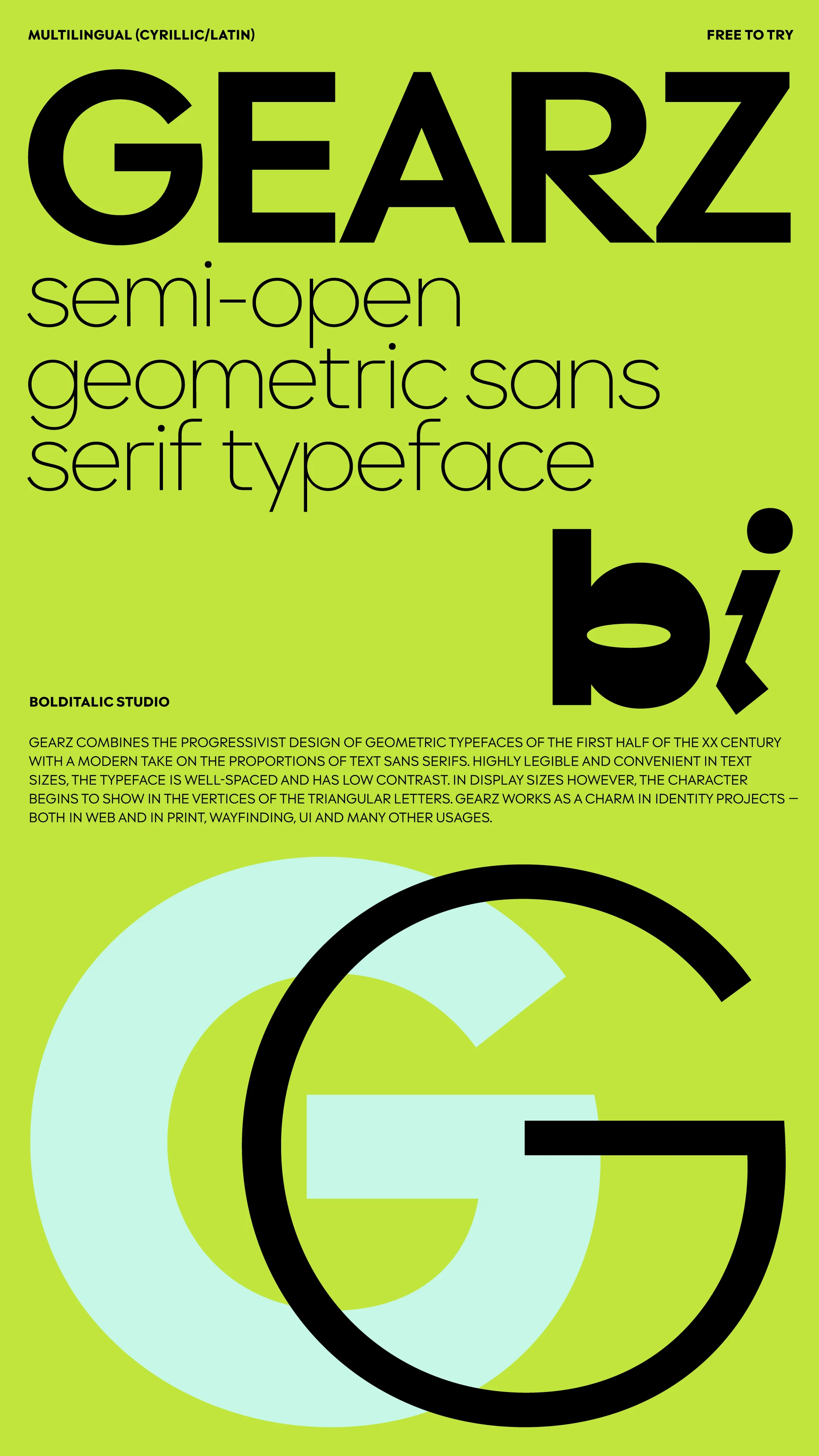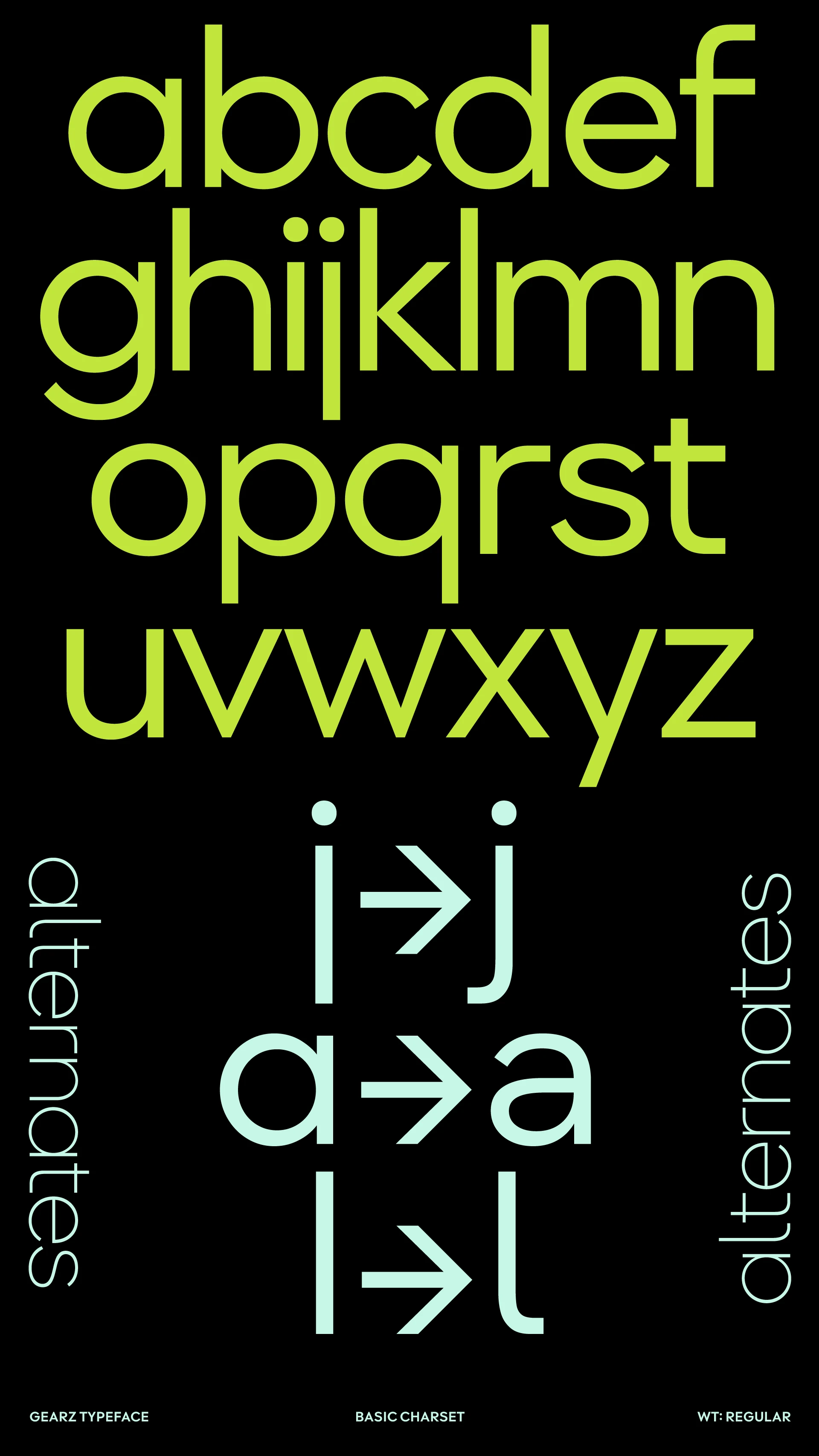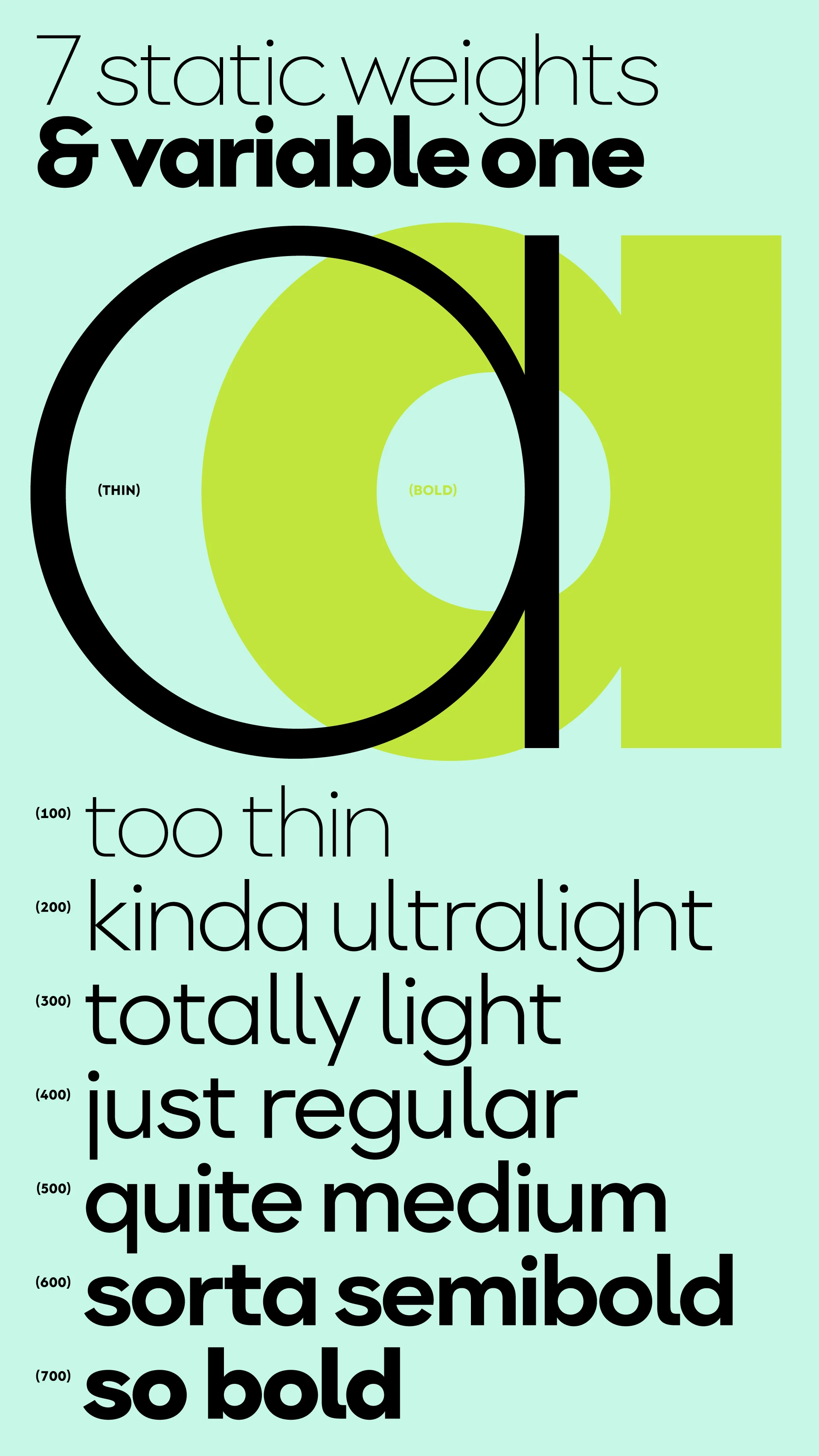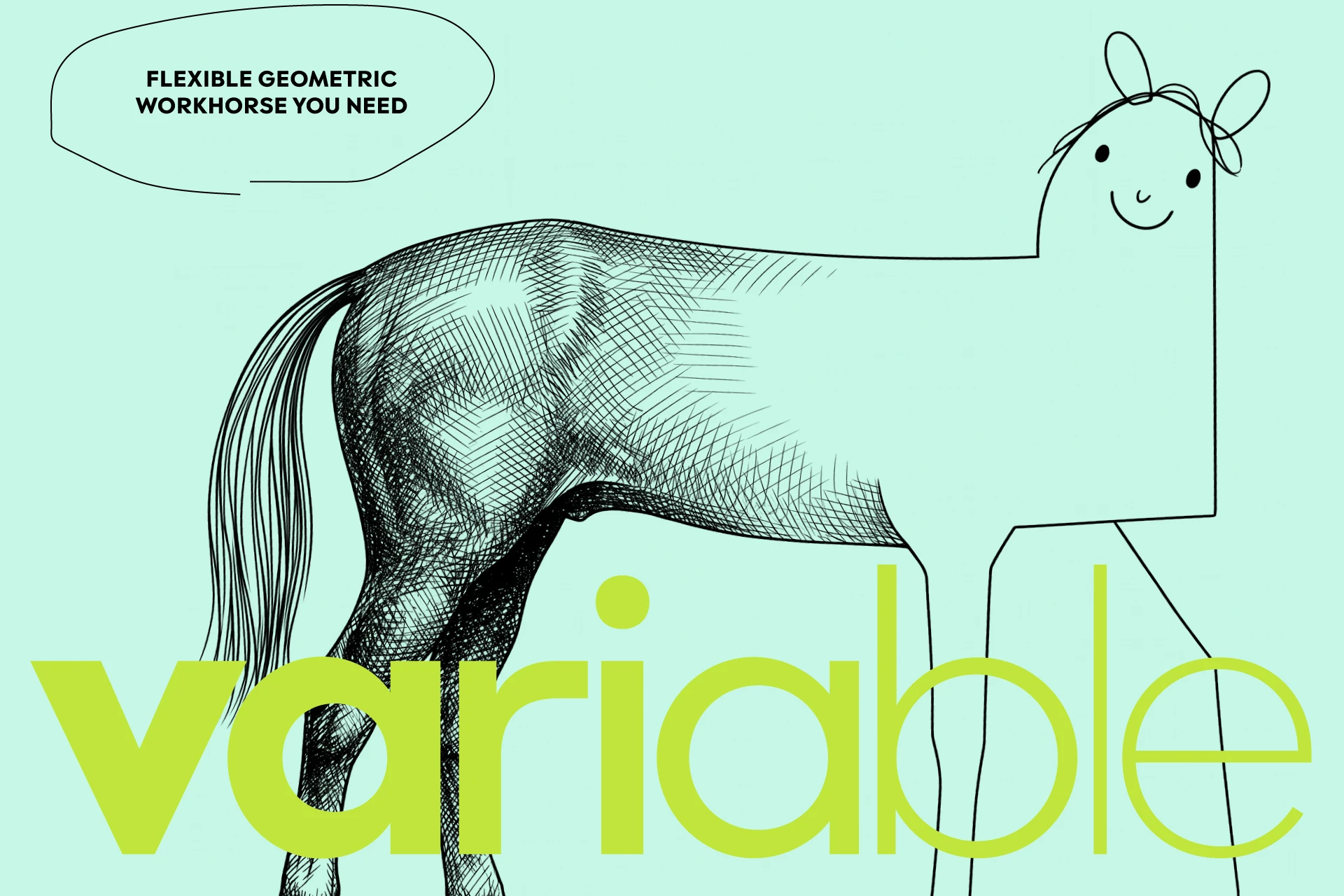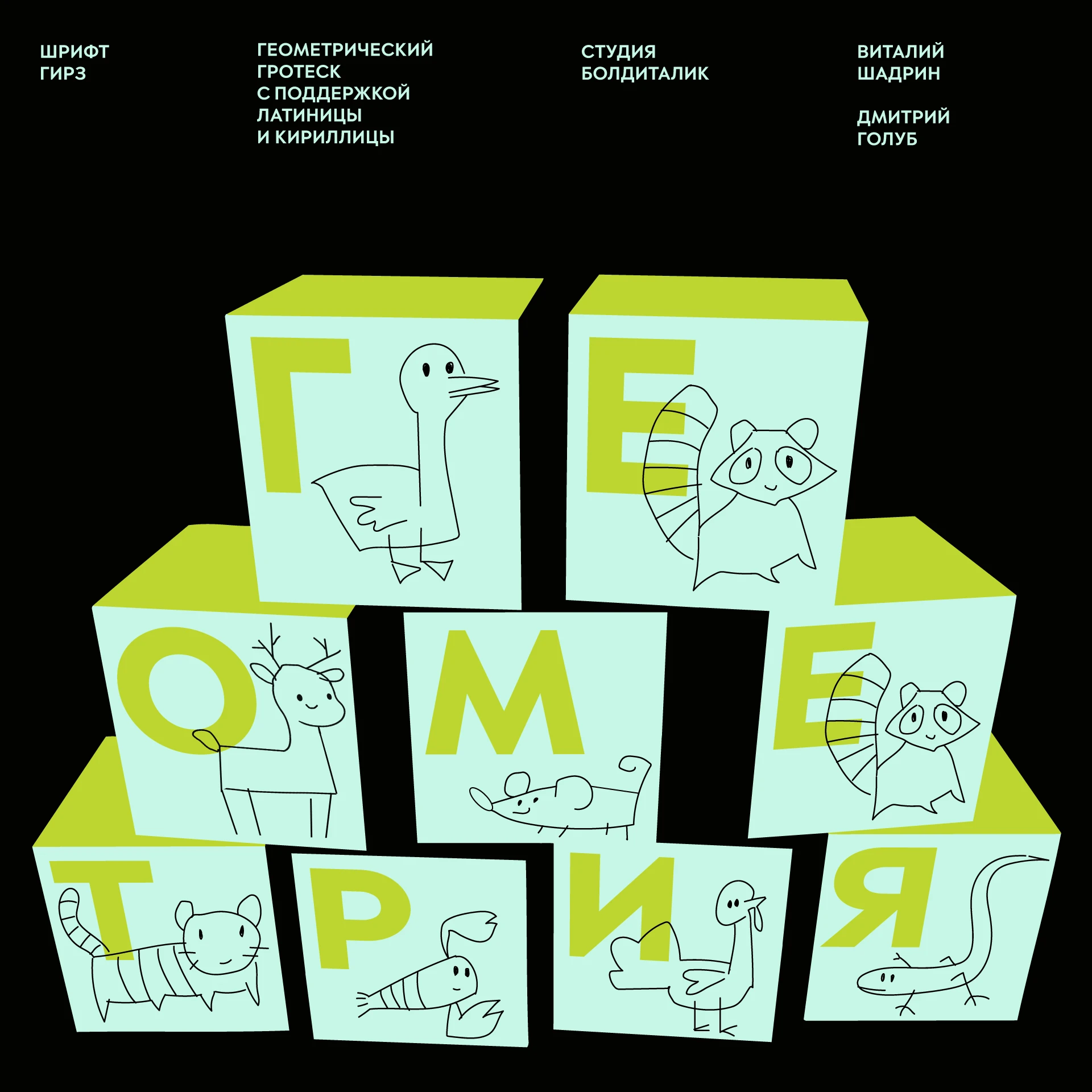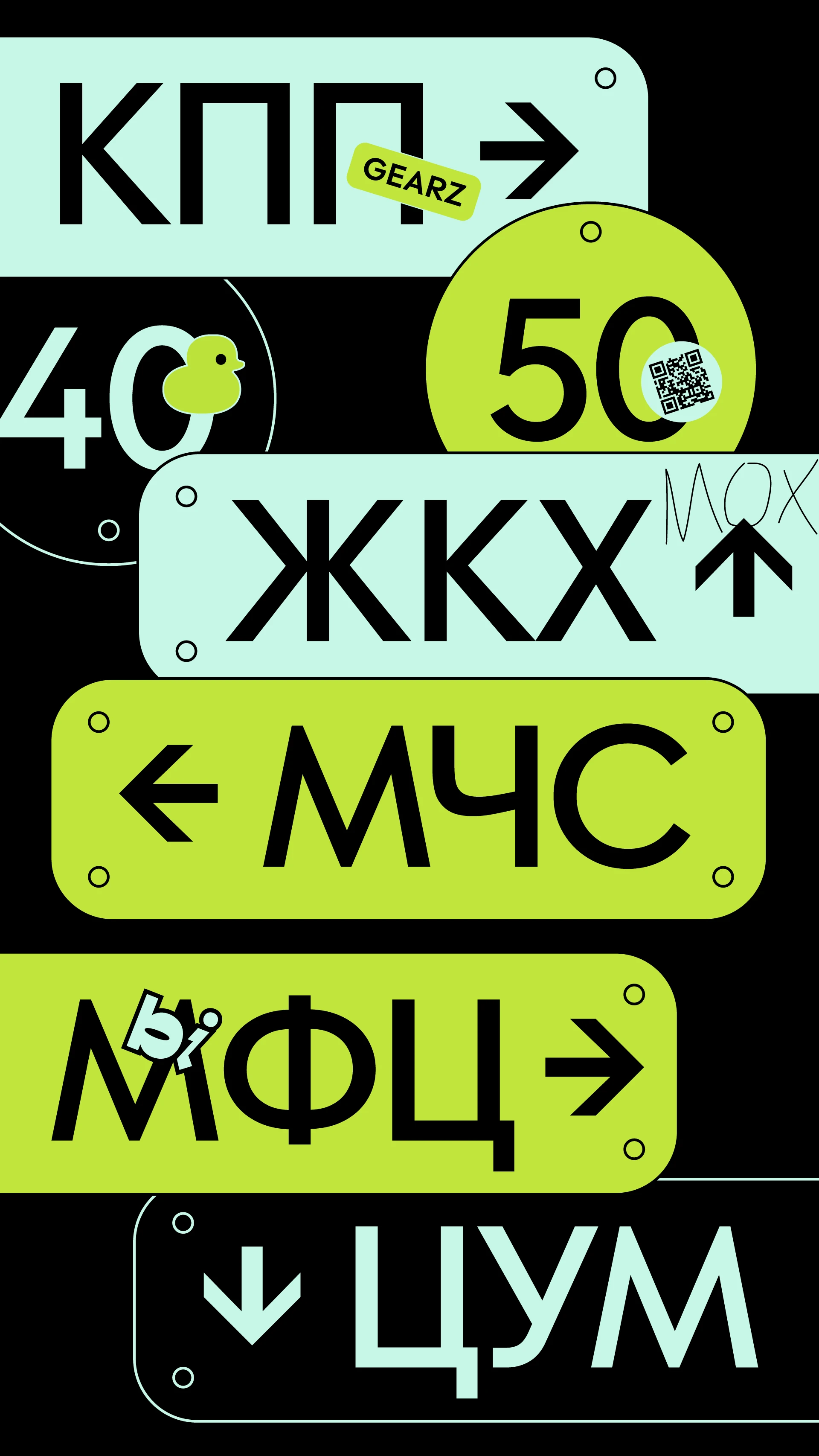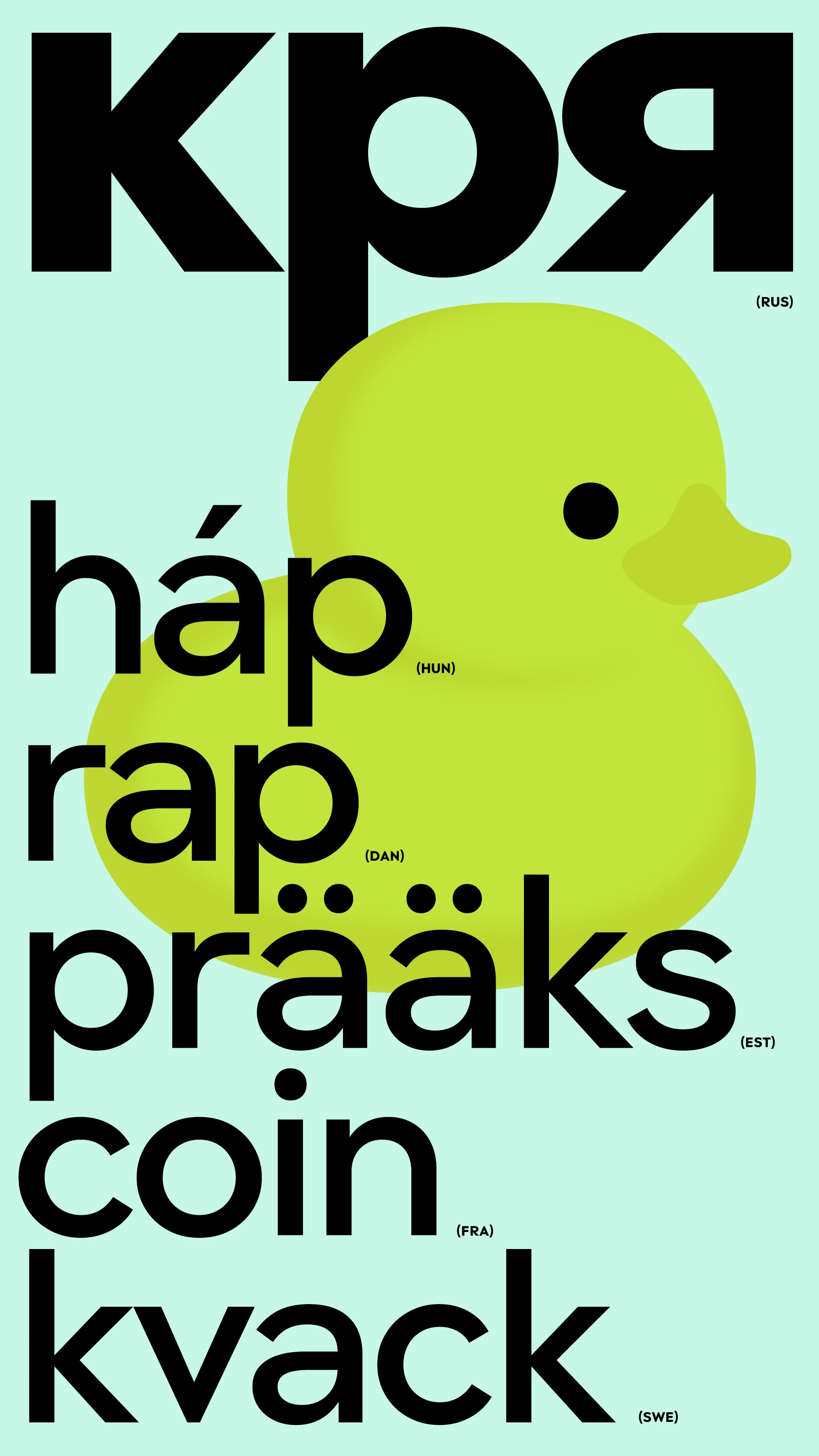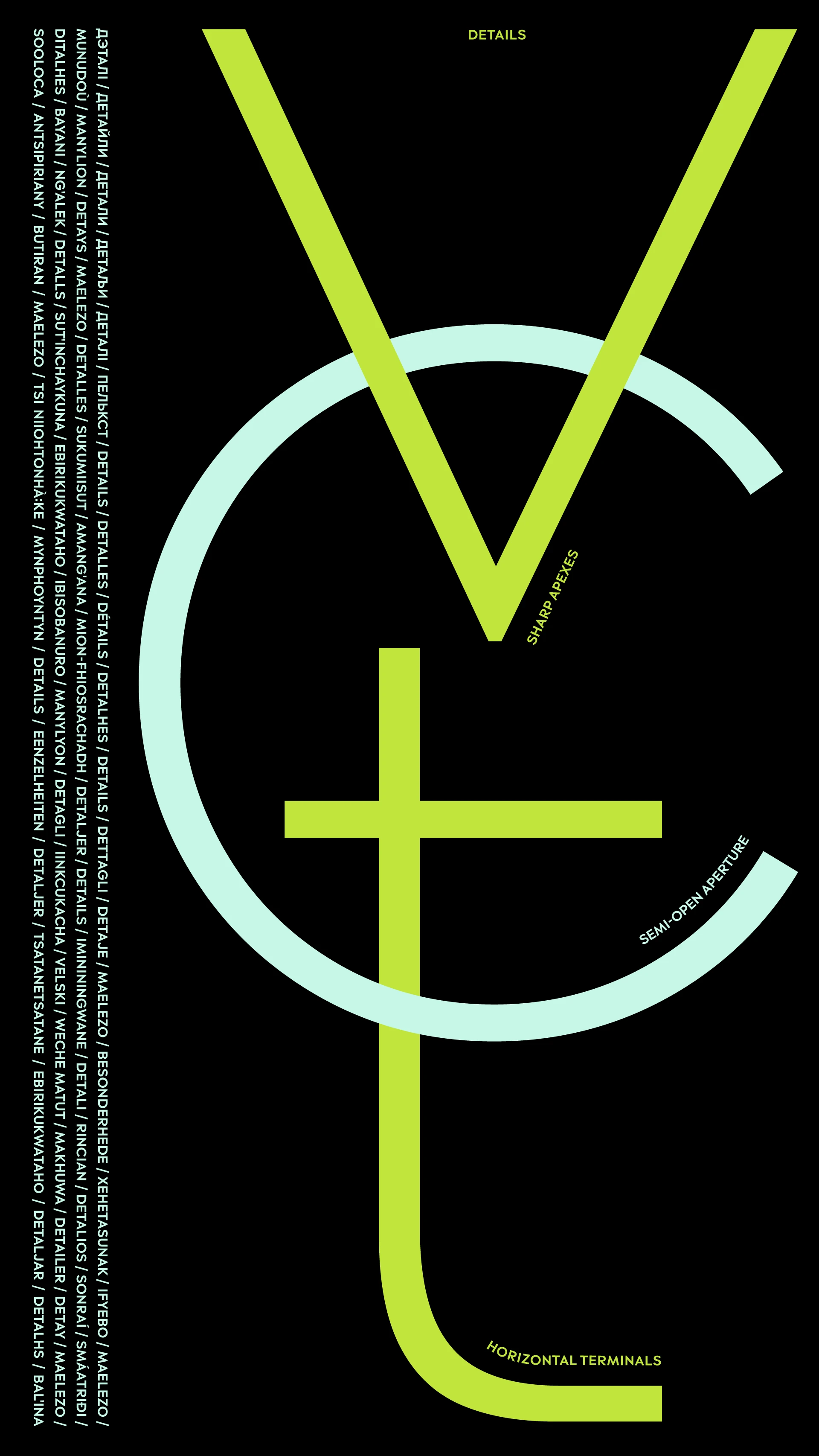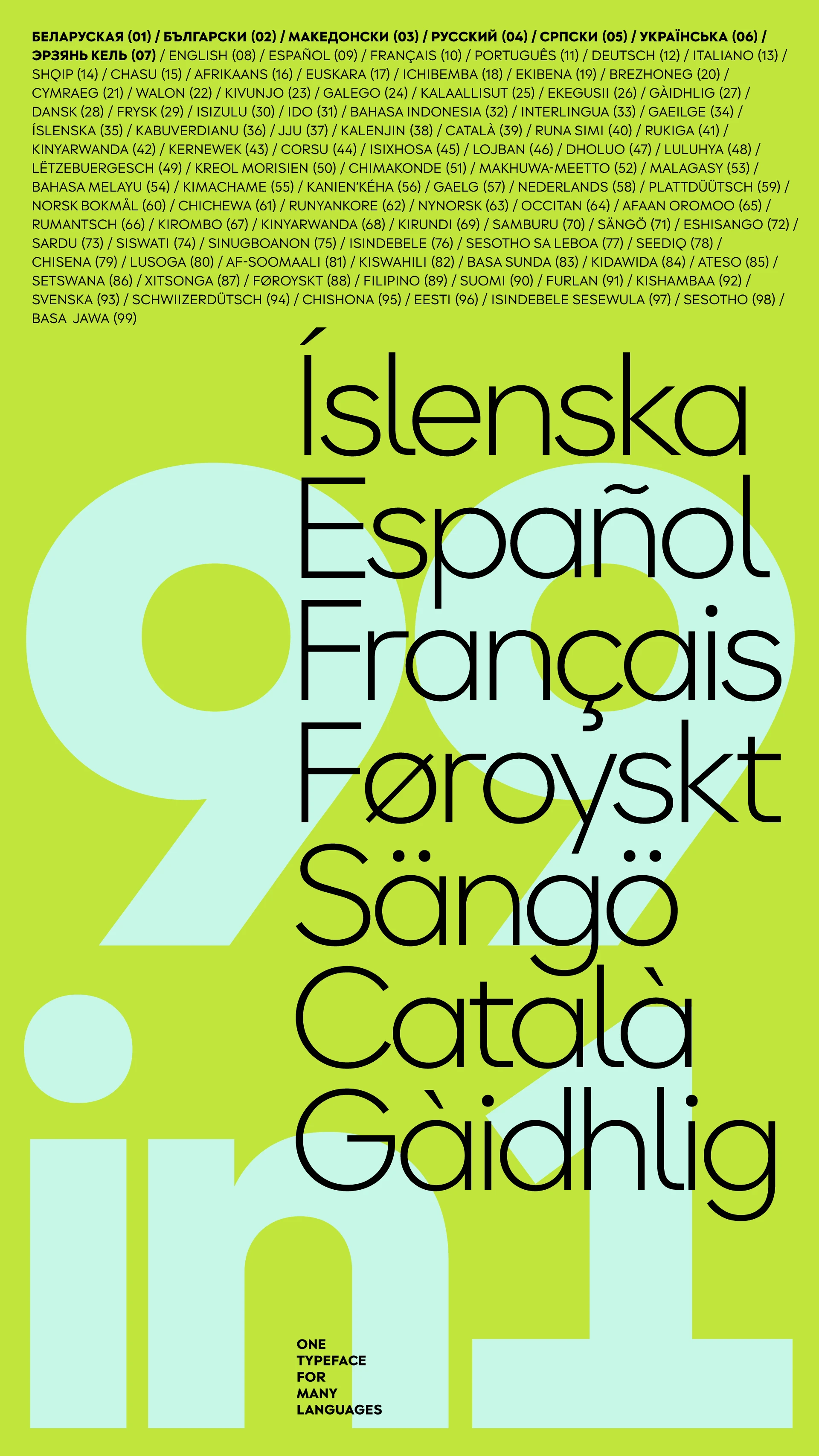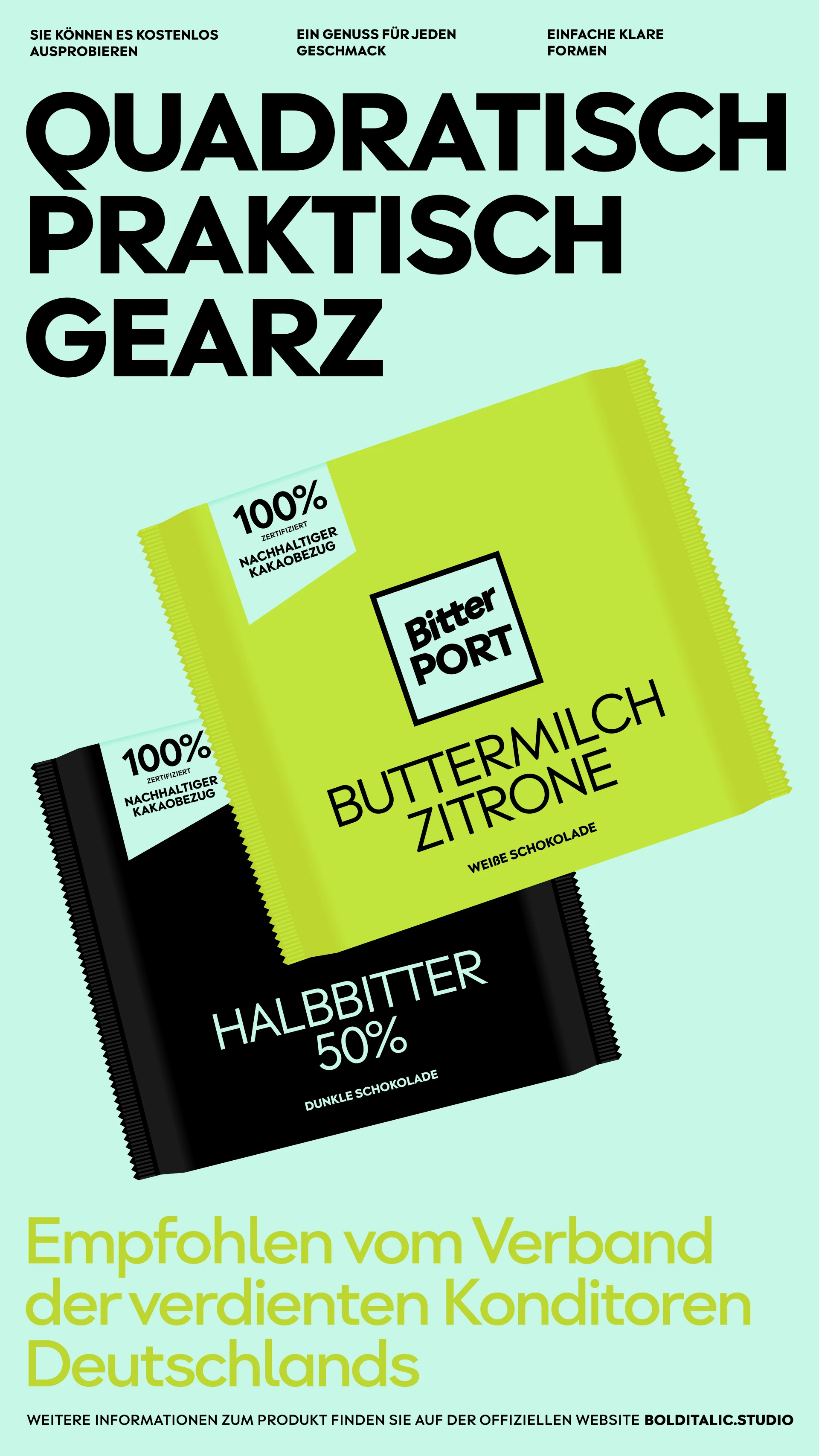
Gearz Typeface
Гирз — геометрический гротеск с умеренно открытыми апертурами. Сочетает в себе прогрессивный дизайн геометрических шрифтов первой половины XX века (Neuzeit Grotesk, Erbar Grotesk) с универсальностью современных гротесков. В меньших размерах низкий контраст и визуально равные пропорции знаков обеспечивают высокую разборчивость и нейтральное звучание. В больших размерах проявляются острые вершины, которые привносят в характер шрифта нотку экспрессии. Лаконичный и практичный гротеск для широкого применения.
Шрифтовой дизайнер: Виталий Шадрин
Арт-директор: Дмитрий Голуб